브랜드 로고를 디자인할 때, 적절한 폰트 선택은 브랜드의 이미지와 메시지를 전달하는 핵심적인 부분입니다. 다양한 한글과 영문 폰트 중에서 특히 브랜드의 콘셉트와 어울리는 폰트를 골라내는 것은 중요한 작업입니다. 아래는 브랜드 로고 디자인에 적합한 몇 가지 한글과 영문 폰트를 추천합니다.
한글 폰트 추천
- 경기천년바탕체
- 특징: 정적이고 차분하며 어른스러운 느낌을 주는 폰트입니다.
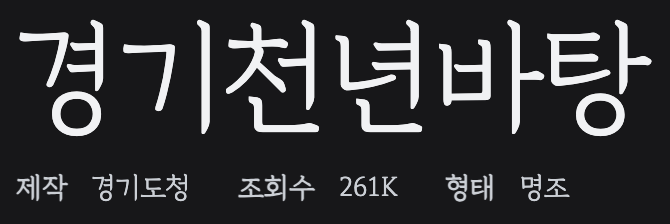
- 말싸미815체
- 특징: 힙하고 옛스러운 레트로 풍의 느낌이 나면서 임팩트 있는 굵은 폰트입니다.
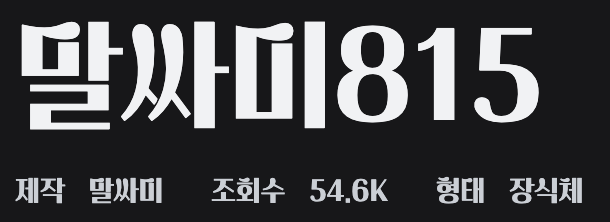
- 포천막거리체
- 특징: 길게 연결하여 늘어뜨린 듯한 차분하고 여유로운 필기체의 느낌을 주는 폰트입니다.
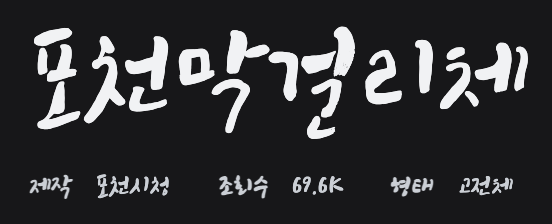
- 디자인하우스체
- 특징: 디자이너들이 사랑하는 폰트로, 딱 떨어지는 듯한 로고들과 아주 잘 어울리는 스타일입니다.
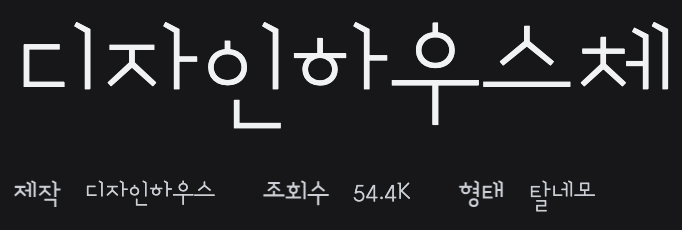
영문 폰트 추천
- Avenir
- 특징: 기하학 폰트로 분류되지만 한계를 뛰어넘는 세련된 스타일을 제공합니다.
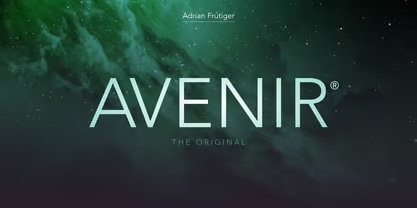
- Agentur
- 특징: 현대적이면서도 전통적인 캘리그래픽 스타일을 결합한 유형입니다.
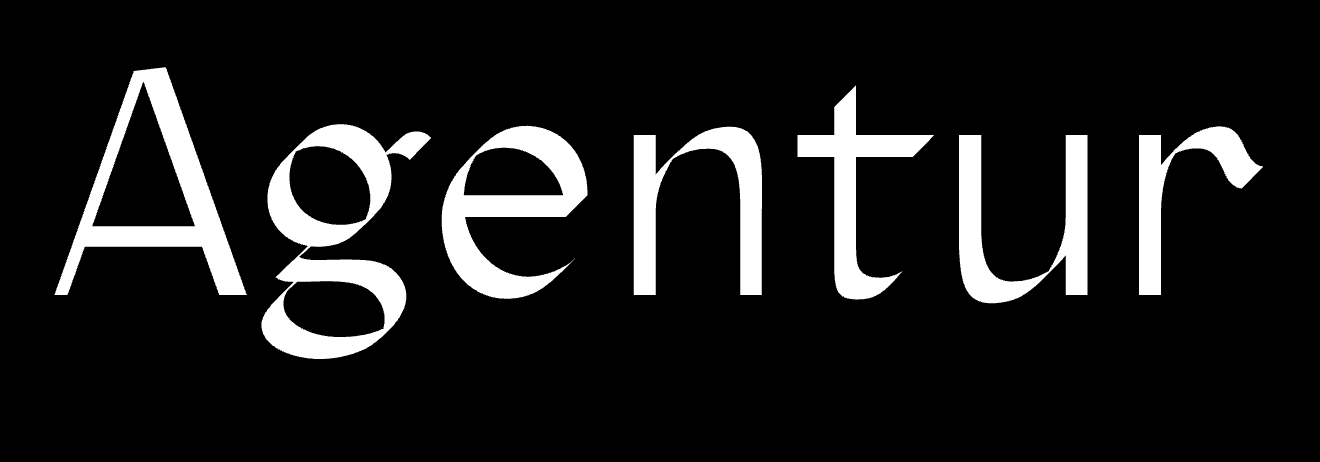
- Canela
- 특징: 세리프도 산세리프도 아닌 특이한 디자인으로 세련되게 설계된 텍스트 로고에 적합합니다.
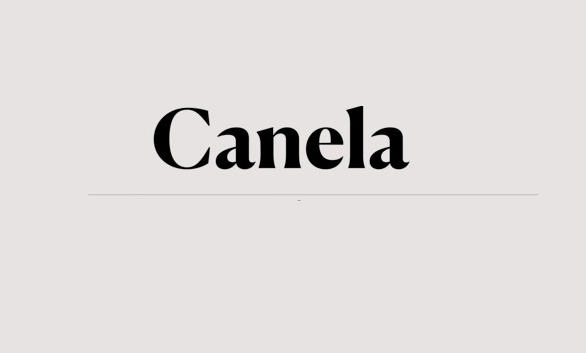
- Separat
- 특징: 강렬한 개성을 더할 수 있는 독특한 폰트입니다.
- GT America
- 특징: 미국과 스위스의 전통적인 디자인에서 영감을 받은 그로테스크 산세리프 폰트입니다.
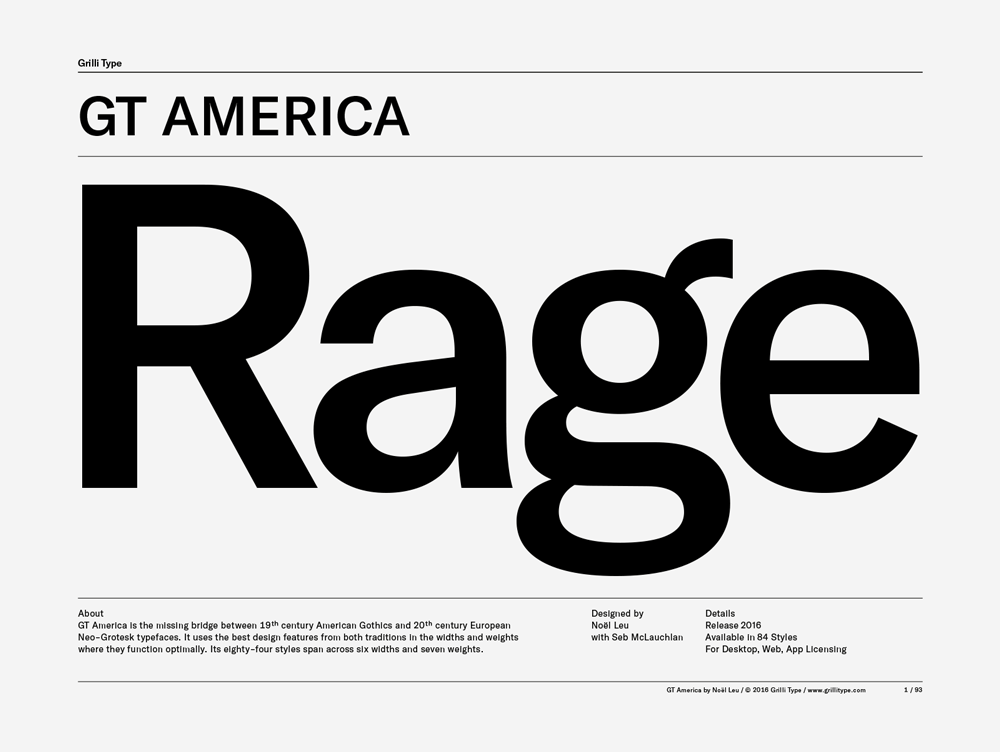
- Futura
- 특징: 거의 100년 전에 출시되었지만 여전히 매우 인기 있는 폰트로 자리잡고 있습니다.